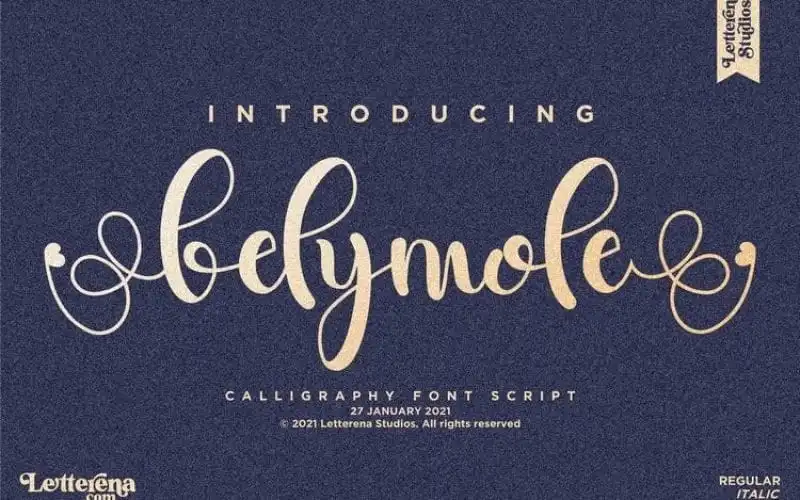
Belymole Calligraphy Font – Download Grátis
A Belymole Calligraphy Font é uma elegante tipografia feita à mão que traz uma sensação de delicadeza e fluidez. Ela foi criada pela Letterena Studios para atender a um vasto range de projetos, desde identidades corporativas até editoriais, passando por camisetas personalizadas, selinhos para fotografias, tags em pacotes de produtos e embalagens de chá. Suas linhas elegantes combinam com diversos estilos de design, tornando-a uma escolha perfeita para qualquer projeto que busque um toque refinado e sofisticado. Numa era cada vez mais digitalizada, a Belymole Calligraphy Font oferece aos designers o equilíbrio perfeito entre modernidade e tradição em seus trabalhos. Seja você um designer de identidades corporativas, criador de produtos ou simplesmente alguém que busca dar um toque personalizado à sua arte, essa fonte é seu companheiro ideal para aprimorar suas habilidades gráficas.